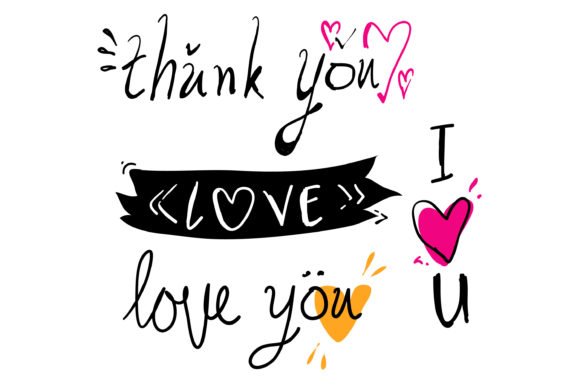
Doodle Label Text Typography Love
Si buscas recursos de alta calidad como Doodle Label Text Typography Love, este paquete premium es una opción fantástica para tus proyectos creativos.
Ya sea que estés creando productos POD (impresión bajo demanda), invitaciones de boda o gráficos para redes sociales, Doodle Label Text Typography Love es una opción ideal.